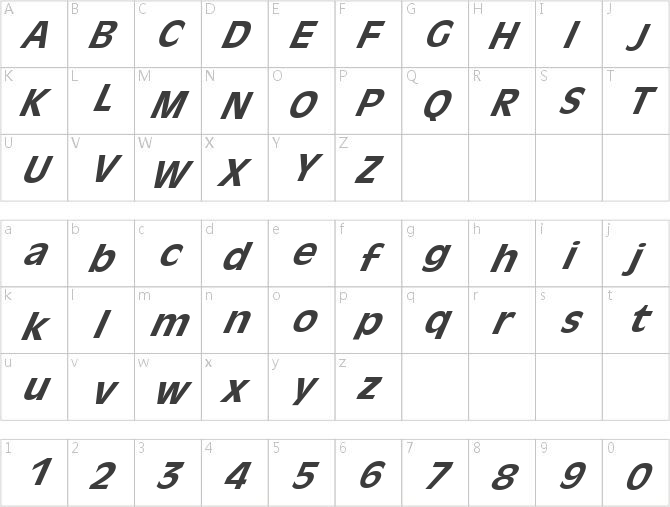
FZ BASIC 1 ITALIC 詳情頁(yè)
FZ BASIC 1 ITALIC字體字庫(kù)是一款讓人賞心悅目、百看不厭的英文字體,適合各類廣告和產(chǎn)品包裝設(shè)計(jì)應(yīng)用,字體大小0.04MB,格式為ttf字體,上傳用戶是曉語(yǔ)無(wú)聲,作者/版權(quán)方為未知